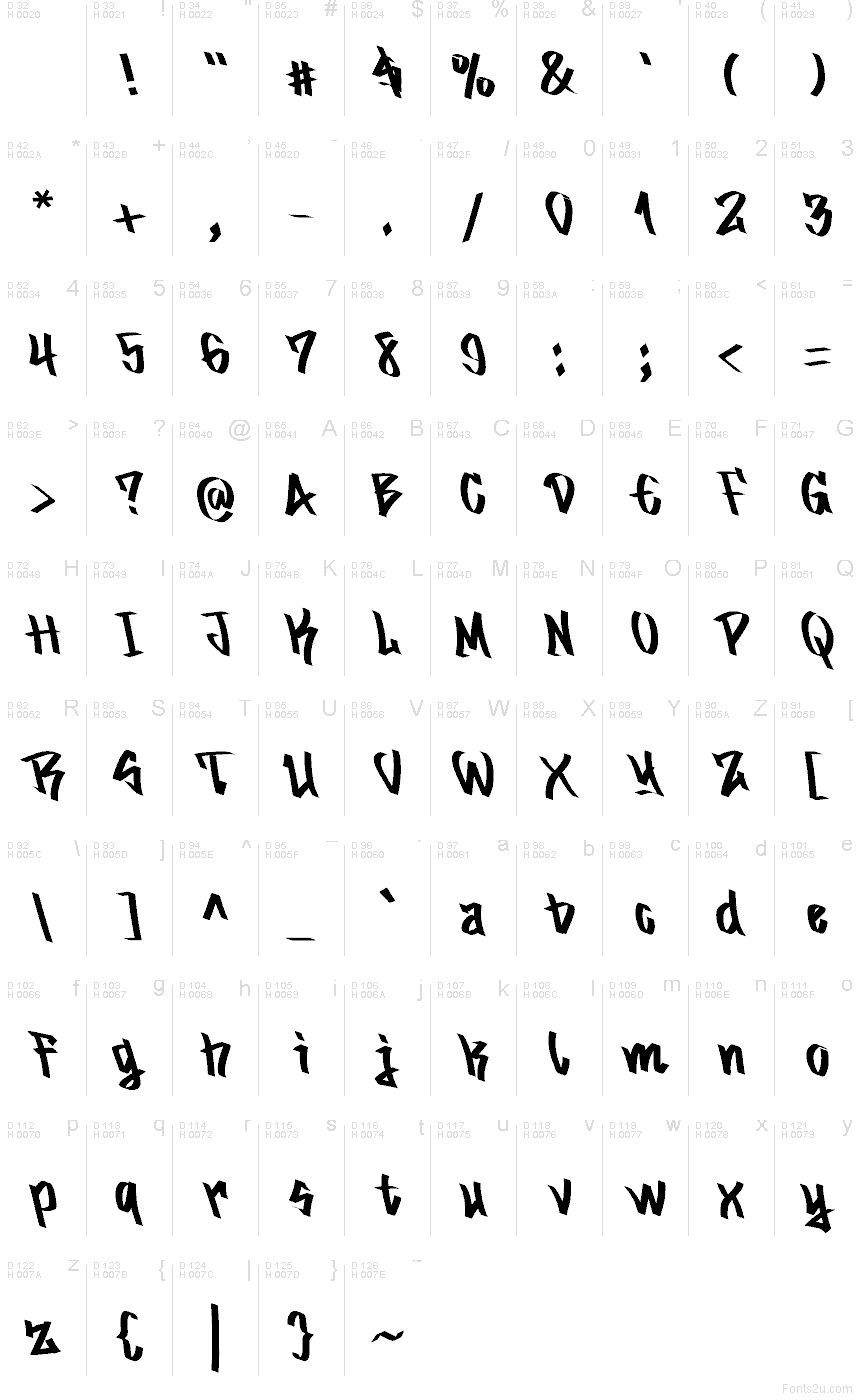
Street Conflict
Street Conflict від Hello Good Studio - це безкоштовний графіті-шрифт із гострими кутастими лініями та ритмом, що нагадує вуличні теги. Букви із загостреними з’єднаннями та скошеними краями надають дизайну зухвалого, «ручного» характеру, що суттєво відрізняється від звичних вивірених шрифтів.
Street Conflict чудово підходить для плакатів, обкладинок альбомів, скейтерських принтів, брендингу у стилі streetwear та рекламних флаєрів: його рвані форми ідеально передають енергетику балонної фарби. Цей безкоштовний шрифт також добре виглядає в логотипах та заголовках, якщо ви прагнете підкреслити сирий, міський та прямий стиль.